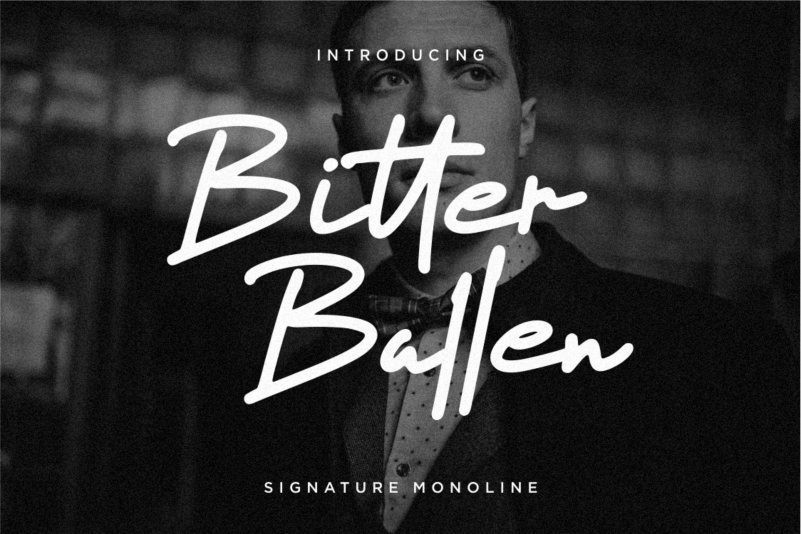
Bitter Ballen Font – Fonte Grátis
Bitter Ballen Font
Esta é uma fonte Monoline criada para destaque. Bitter Ballen foi projetado perfeitamente para aplicativos que exigem elegância e simplicidade. Seja ela usada na embalagem de produtos, no projeto de marca, revistas, redes sociais, casamentos ou simplesmente para destacar palavras acima do fundo – Bitter Ballen atende a todas essas necessidades. Com seu design limpo e moderno, esta fonte Monoline oferece uma maneira única de expressar sua identidade visual. Suavemente elegante e fácil de ler, ela é ideal para qualquer aplicação que busque um toque único e sofisticado em sua produção gráfica. Não importa o formato ou tamanho da aplicação, Bitter Ballen traz um toque distintivo à sua criação.
Designer: Enigma Lettering Studio